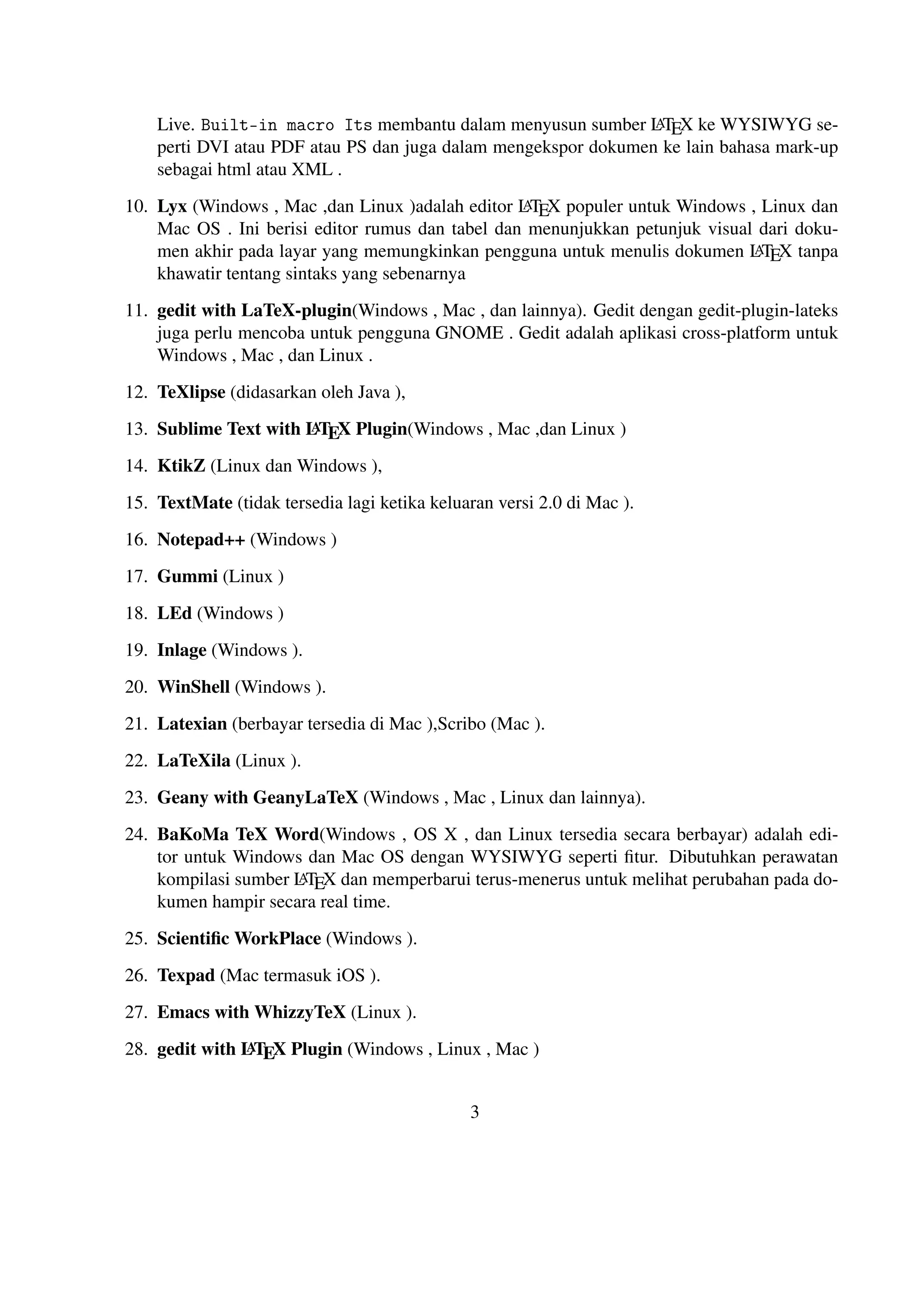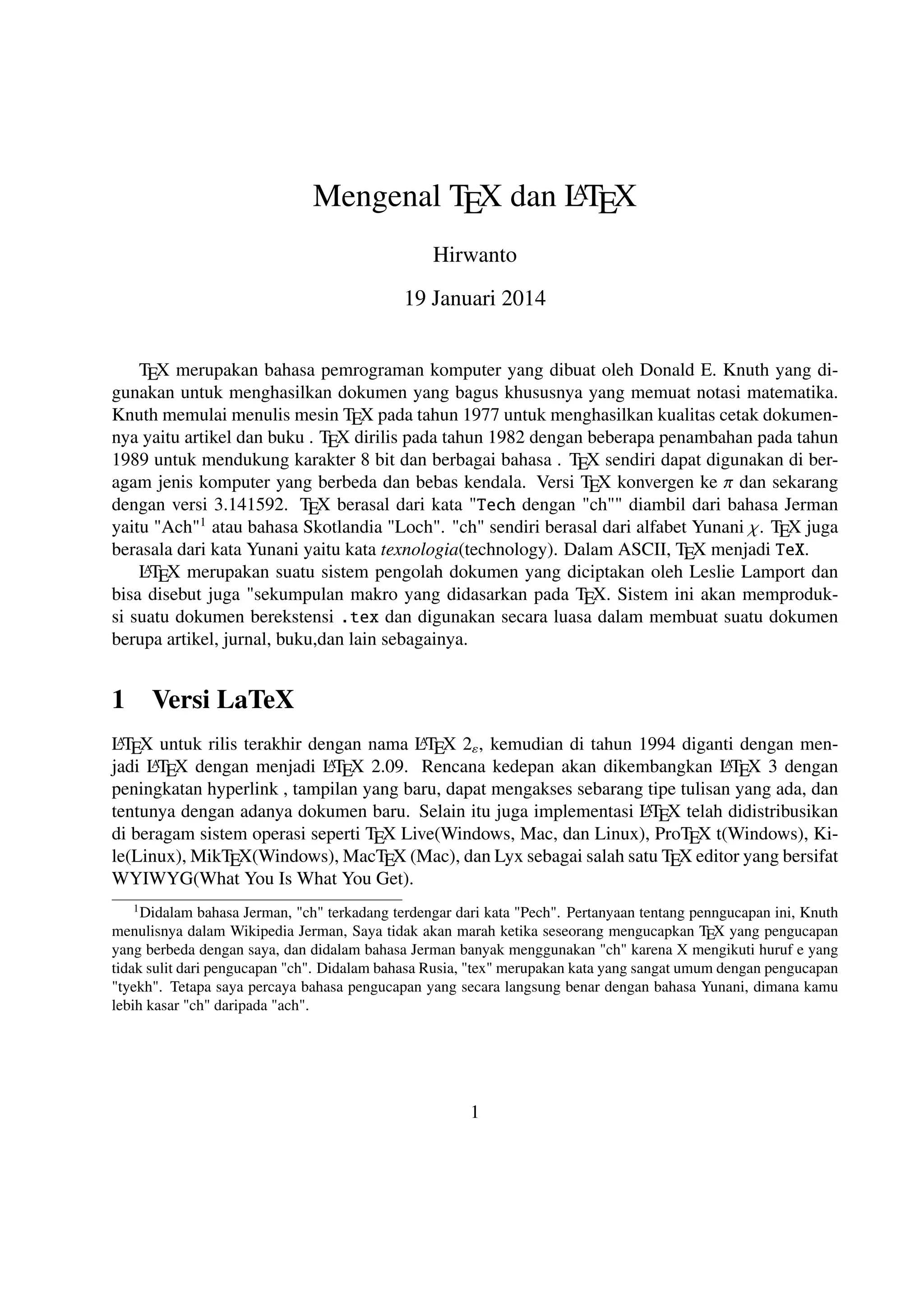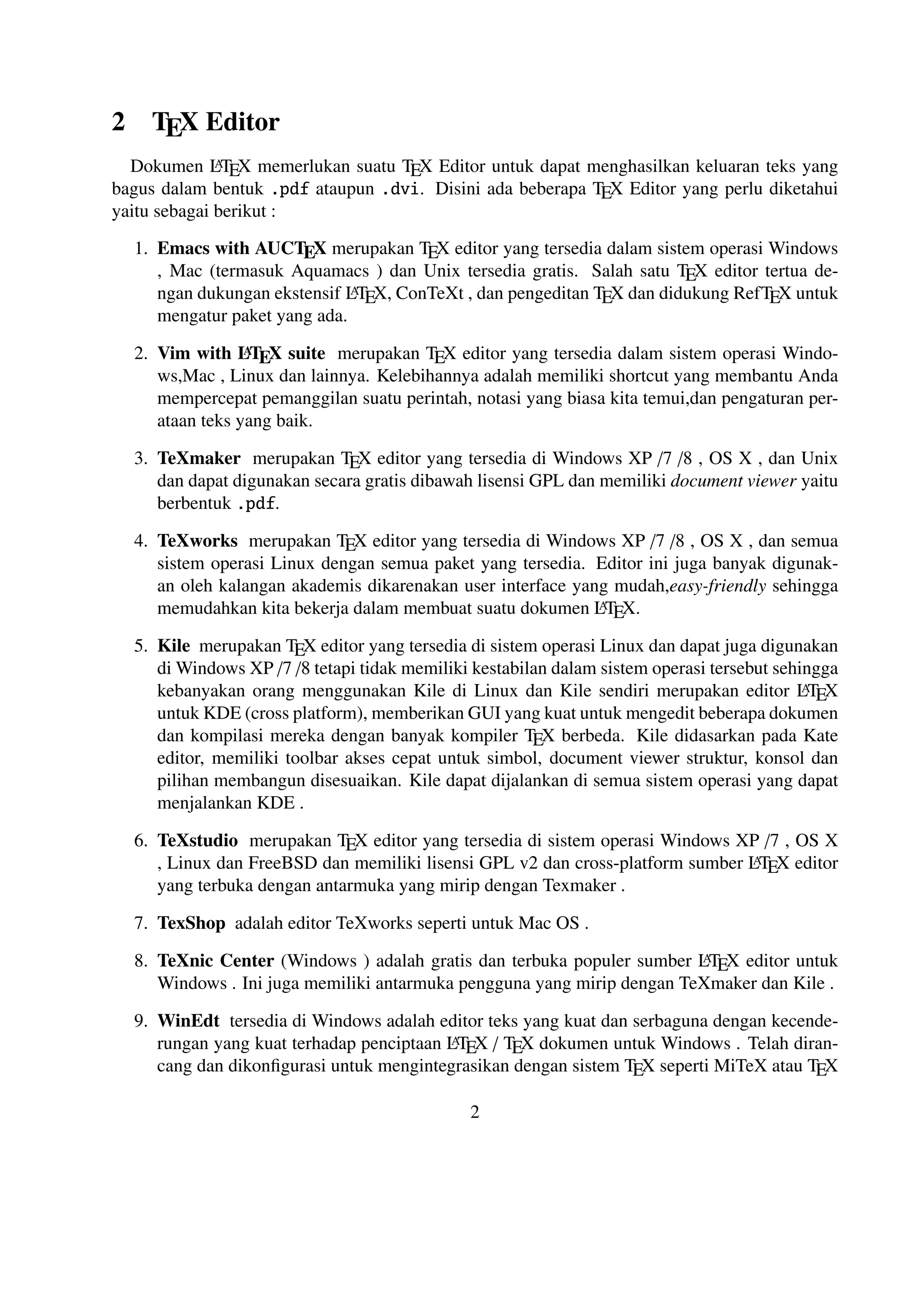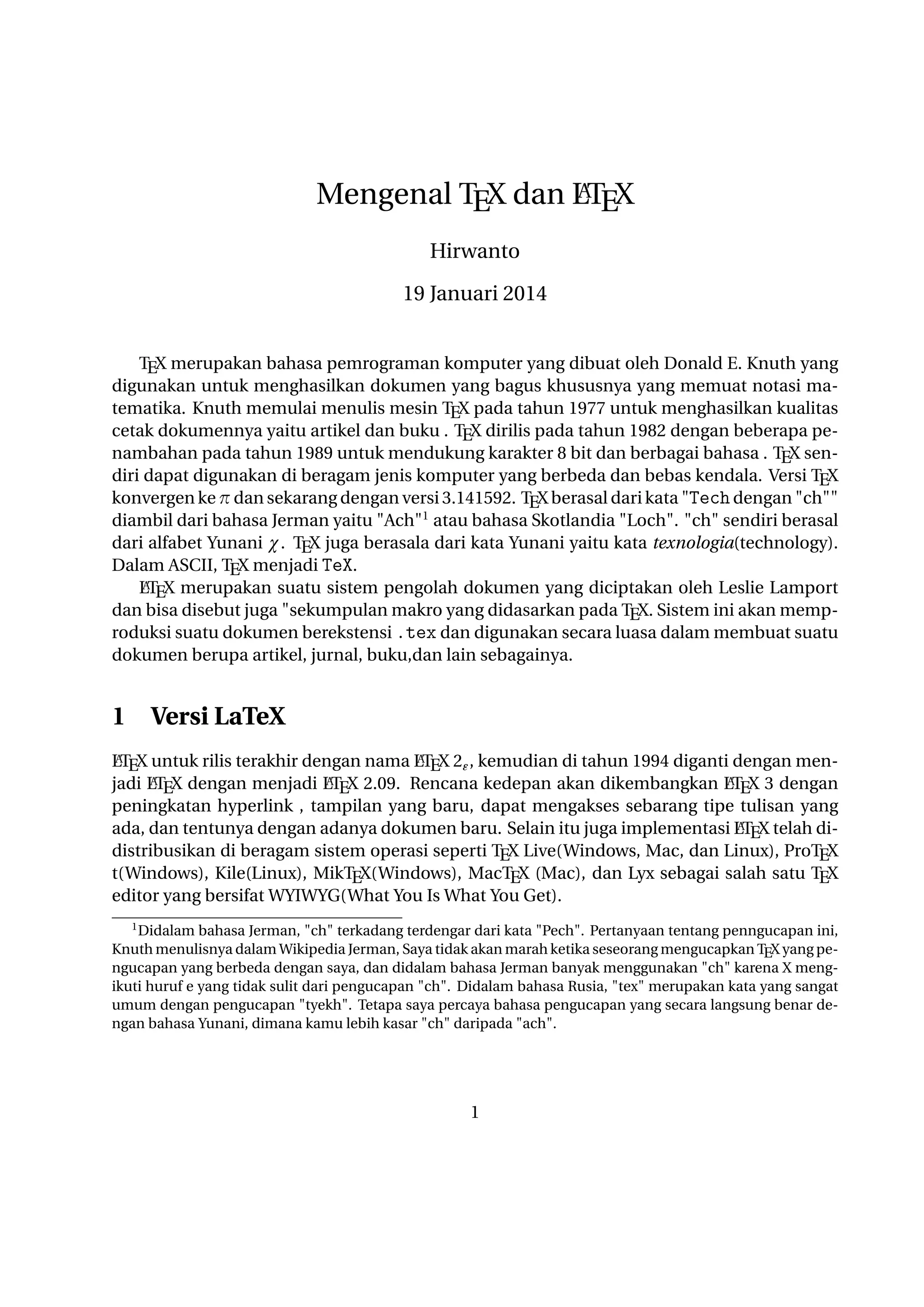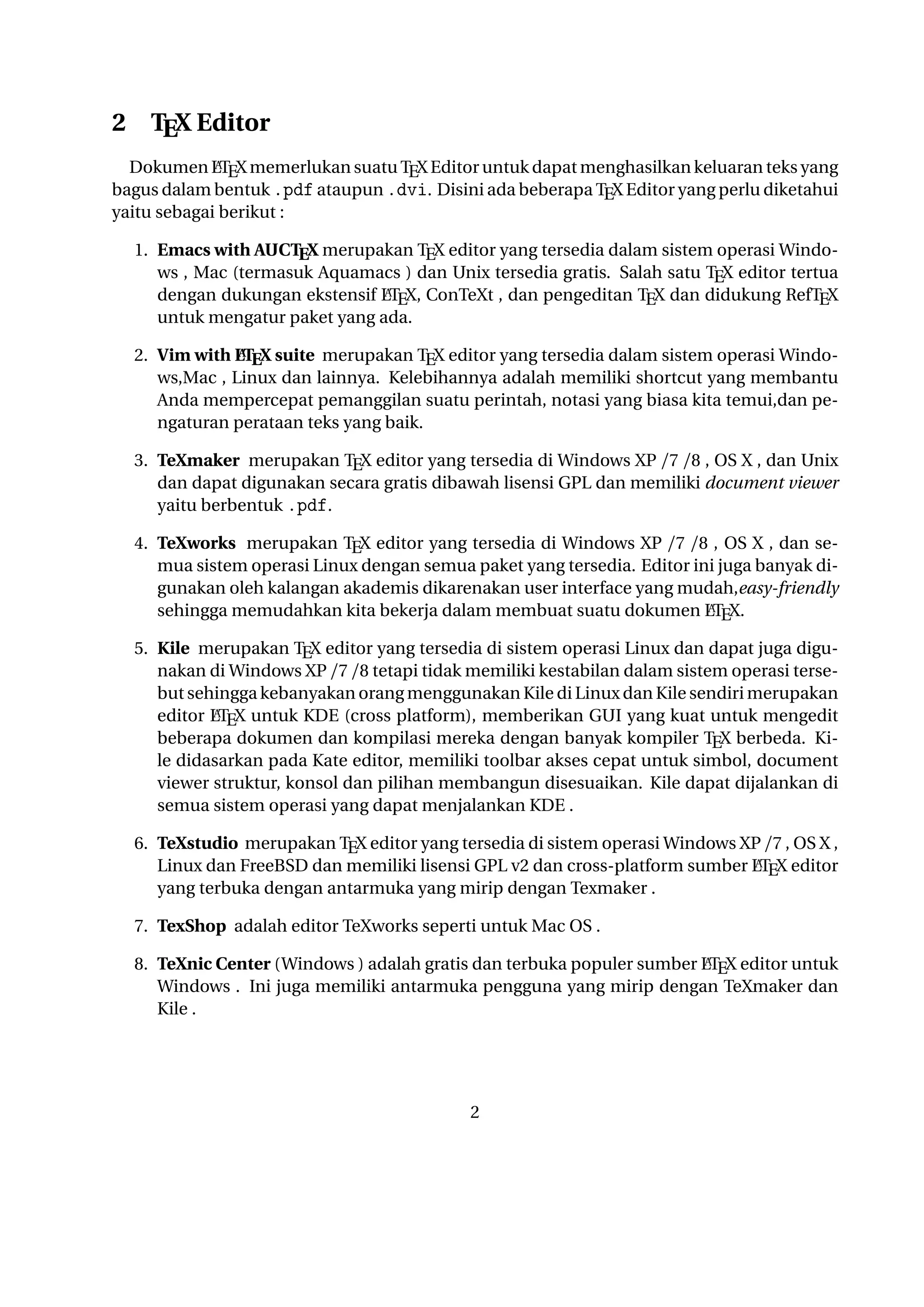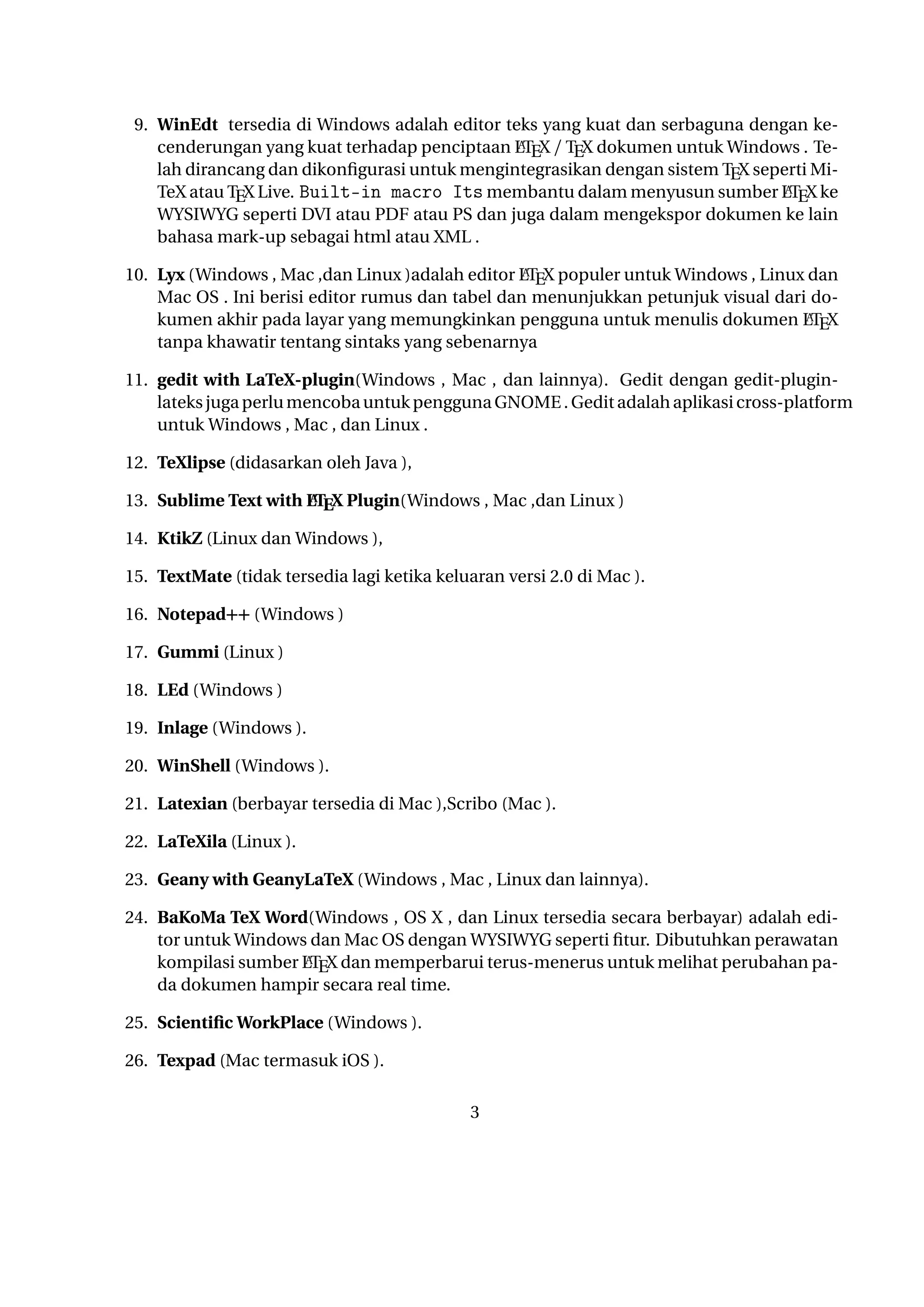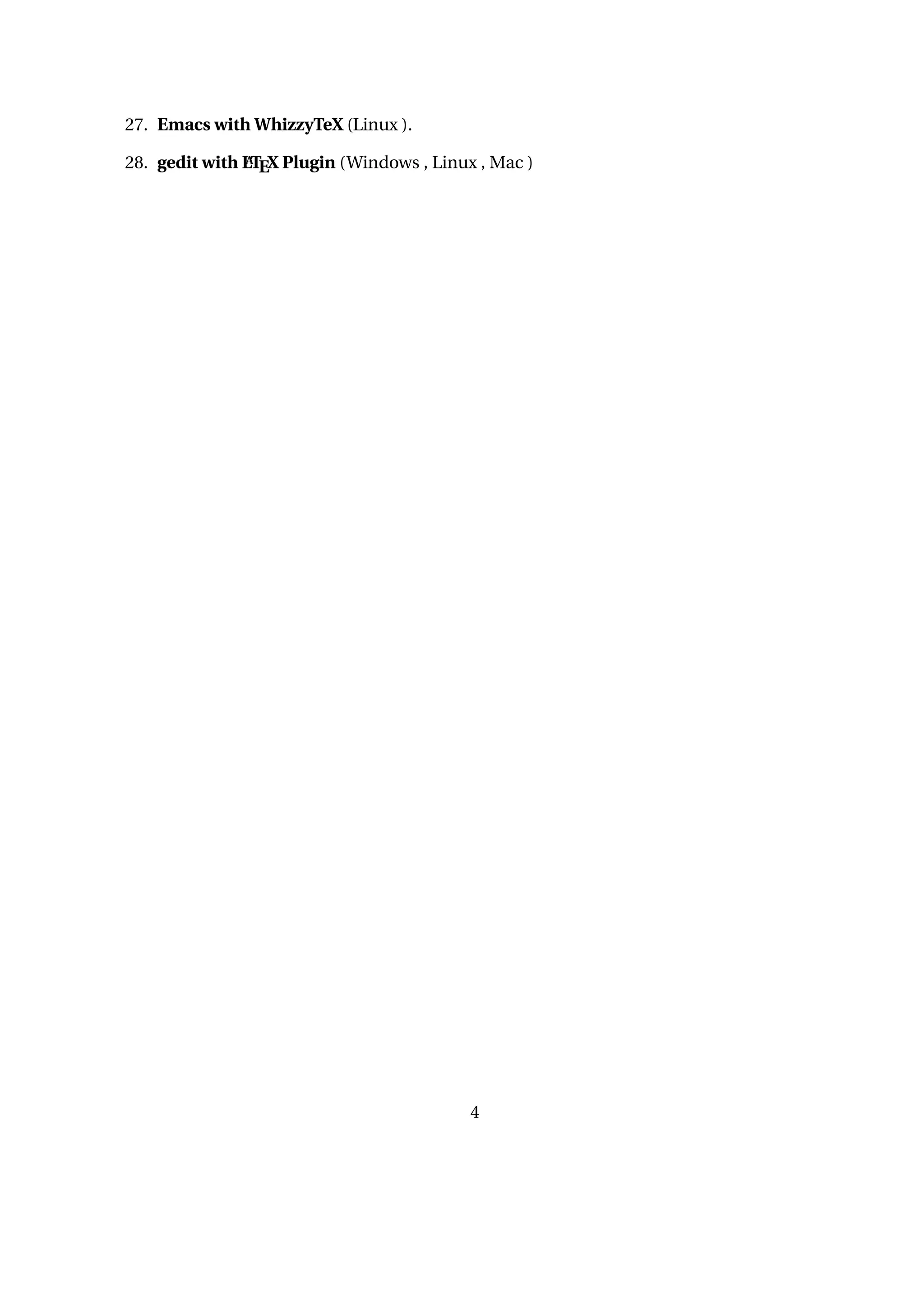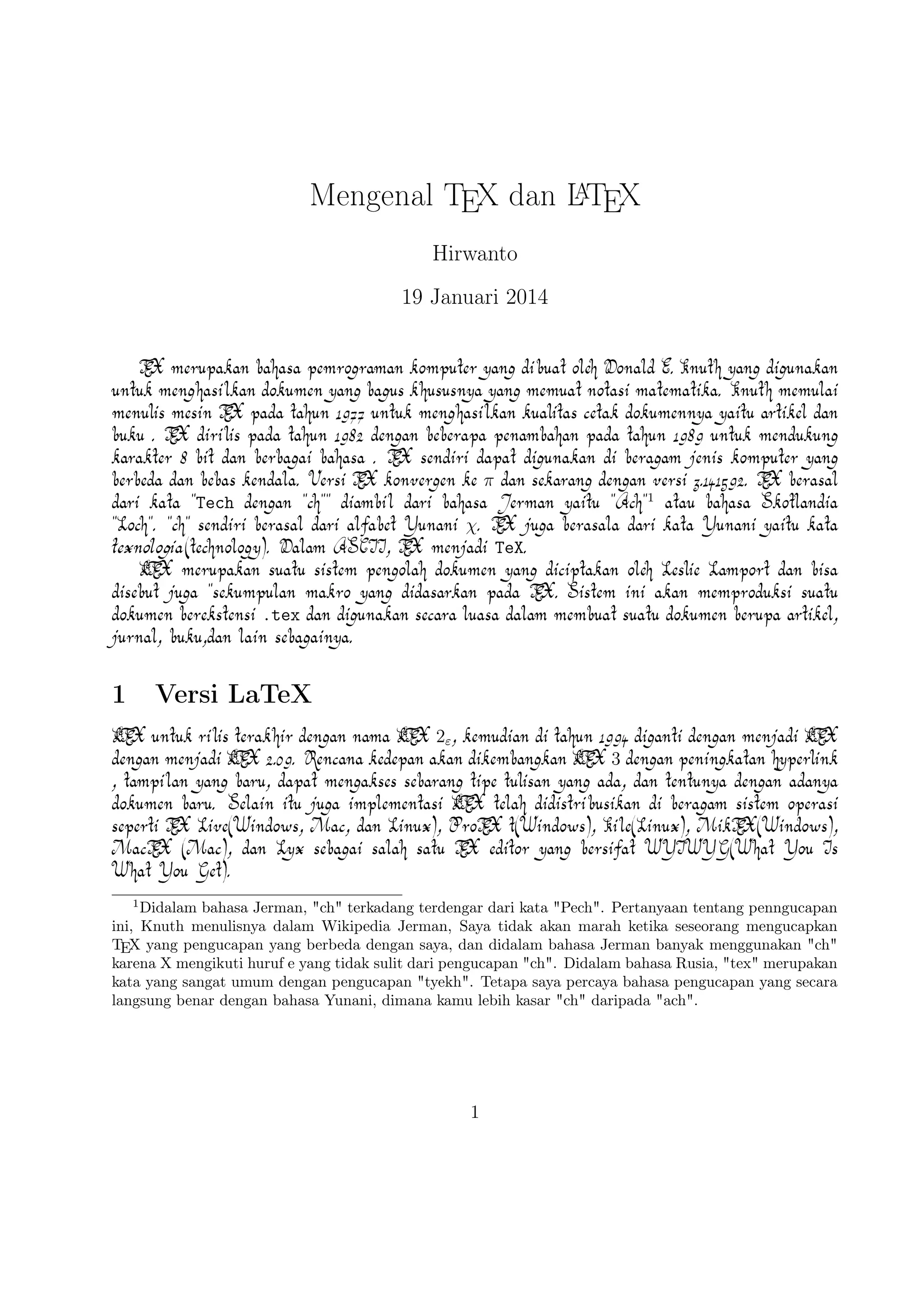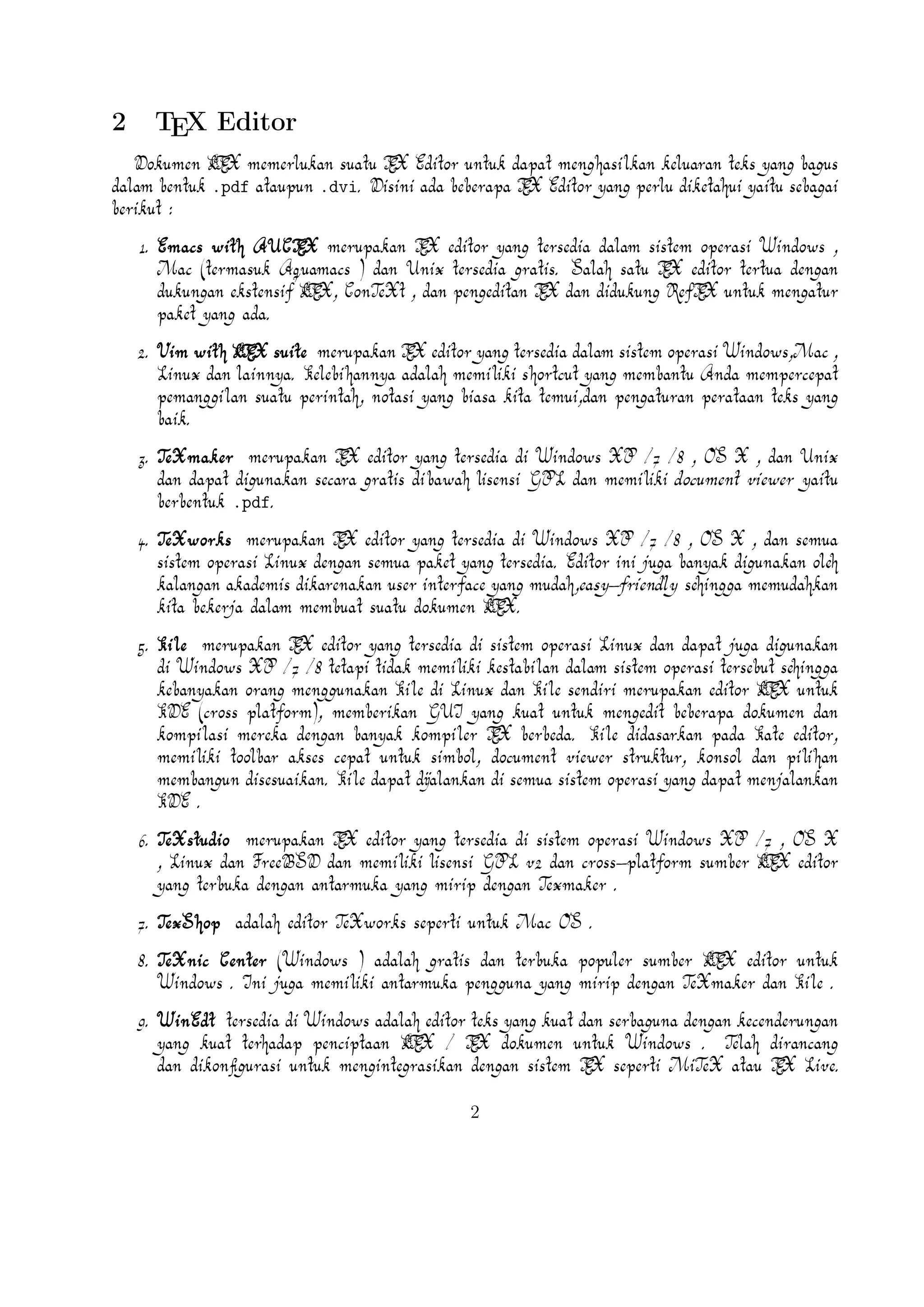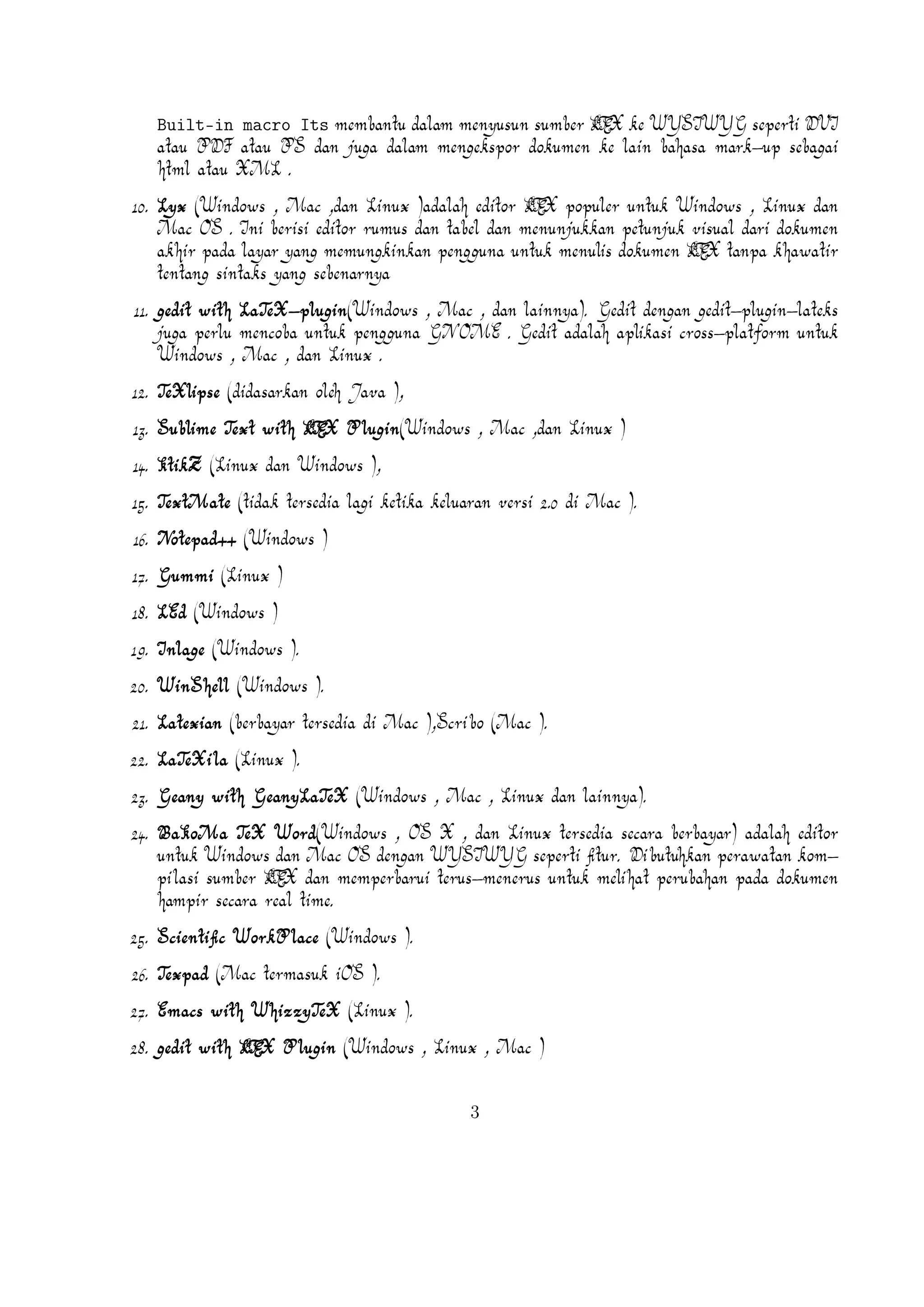
Mengenal TEX dan LTEX
Hirwanto
19 Januari 2014
TEX merupakan bahasa pemrograman komputer yang dibuat oleh Donald E. Knuth yang
digunakan untuk menghasilkan dokumen yang bagus khususnya yang memuat notasi matematika. Knuth memulai menulis mesin TEX pada tahun 1977 untuk menghasilkan kualitas cetak
dokumennya yaitu artikel dan buku . TEX dirilis pada tahun 1982 dengan beberapa penambahan pada tahun 1989 untuk mendukung karakter 8 bit dan berbagai bahasa . TEX sendiri dapat
digunakan di beragam jenis komputer yang berbeda dan bebas kendala. Versi TEX konvergen
ke π dan sekarang dengan versi 3.141592. TEX berasal dari kata "Tech dengan "ch"" diambil
dari bahasa Jerman yaitu "Ach"1 atau bahasa Skotlandia "Loch". "ch" sendiri berasal dari alfabet
Yunani χ. TEX juga berasala dari kata Yunani yaitu kata texnologia(technology). Dalam ASCII,
TEX menjadi TeX.
A
LTEX merupakan suatu sistem pengolah dokumen yang diciptakan oleh Leslie Lamport dan
bisa disebut juga "sekumpulan makro yang didasarkan pada TEX. Sistem ini akan memproduksi
suatu dokumen berekstensi .tex dan digunakan secara luasa dalam membuat suatu dokumen
berupa artikel, jurnal, buku,dan lain sebagainya.
Versi LTEX
LTEX untuk rilis terakhir dengan nama LTEX 2ε , kemudian di tahun 1994 diganti dengan menjadi
A X dengan menjadi LT X 2.09. Rencana kedepan akan dikembangkan LT X 3 dengan peningA
katan hyperlink , tampilan yang baru, dapat mengakses sebarang tipe tulisan yang ada, dan
tentunya dengan adanya dokumen baru. Selain itu juga implementasi LTEX telah didistribusikan di beragam sistem operasi seperti TEX Live(Windows, Mac, dan Linux), ProTEX t(Windows),
Kile(Linux), MikTEX(Windows), MacTEX (Mac), dan Lyx sebagai salah satu TEX editor yang bersifat WYIWYG(What You Is What You Get).
Didalam bahasa Jerman, "ch" terkadang terdengar dari kata "Pech". Pertanyaan tentang penngucapan ini, Knuth
menulisnya dalam Wikipedia Jerman, Saya tidak akan marah ketika seseorang mengucapkan TEX yang pengucapan
yang berbeda dengan saya, dan didalam bahasa Jerman banyak menggunakan "ch" karena X mengikuti huruf e
yang tidak sulit dari pengucapan "ch". Didalam bahasa Rusia, "tex" merupakan kata yang sangat umum dengan
pengucapan "tyekh". Tetapa saya percaya bahasa pengucapan yang secara langsung benar dengan bahasa Yunani,
dimana kamu lebih kasar "ch" daripada "ach".
TEX Editor
Dokumen LTEX memerlukan suatu TEX Editor untuk dapat menghasilkan keluaran teks yang
bagus dalam bentuk .pdf ataupun .dvi. Disini ada beberapa TEX Editor yang perlu diketahui
yaitu sebagai berikut :
1. Emacs with AUCTEX merupakan TEX editor yang tersedia dalam sistem operasi Windows
, Mac (termasuk Aquamacs ) dan Unix tersedia gratis. Salah satu TEX editor tertua dengan
dukungan ekstensif LTEX, ConTeXt , dan pengeditan TEX dan didukung RefTEX untuk
mengatur paket yang ada.
2. Vim with LTEX suite merupakan TEX editor yang tersedia dalam sistem operasi Windows,Mac , Linux dan lainnya. Kelebihannya adalah memiliki shortcut yang membantu Anda
mempercepat pemanggilan suatu perintah, notasi yang biasa kita temui,dan pengaturan
perataan teks yang baik.
3. TeXmaker merupakan TEX editor yang tersedia di Windows XP /7 /8 , OS X , dan Unix
yaitu berbentuk .pdf.
4. TeXworks merupakan TEX editor yang tersedia di Windows XP /7 /8 , OS X , dan semua
sistem operasi Linux dengan semua paket yang tersedia. Editor ini juga banyak digunakan
oleh kalangan akademis dikarenakan user interface yang mudah,easy-friendly sehingga
memudahkan kita bekerja dalam membuat suatu dokumen LTEX.
5. Kile merupakan TEX editor yang tersedia di sistem operasi Linux dan dapat juga digunakan di Windows XP /7 /8 tetapi tidak memiliki kestabilan dalam sistem operasi tersebut
sehingga kebanyakan orang menggunakan Kile di Linux dan Kile sendiri merupakan
editor LTEX untuk KDE (cross platform), memberikan GUI yang kuat untuk mengedit
beberapa dokumen dan kompilasi mereka dengan banyak kompiler TEX berbeda. Kile
didasarkan pada Kate editor, memiliki toolbar akses cepat untuk simbol, document viewer
struktur, konsol dan pilihan membangun disesuaikan. Kile dapat dijalankan di semua
sistem operasi yang dapat menjalankan KDE .
6. TeXstudio merupakan TEX editor yang tersedia di sistem operasi Windows XP /7 , OS X
, Linux dan FreeBSD dan memiliki lisensi GPL v2 dan cross-platform sumber LTEX editor
yang terbuka dengan antarmuka yang mirip dengan Texmaker .
7. TexShop adalah editor TeXworks seperti untuk Mac OS .
8. TeXnic Center (Windows ) adalah gratis dan terbuka populer sumber LTEX editor untuk
Windows . Ini juga memiliki antarmuka pengguna yang mirip dengan TeXmaker dan
digunakan untuk menghasilkan dokumen yang bagus khususnya yang memuat notasi matematika. Knuth memulai menulis mesin TEX pada tahun 1977 untuk menghasilkan kualitas
cetak dokumennya yaitu artikel dan buku . TEX dirilis pada tahun 1982 dengan beberapa
penambahan pada tahun 1989 untuk mendukung karakter 8 bit dan berbagai bahasa . TEX
sendiri dapat digunakan di beragam jenis komputer yang berbeda dan bebas kendala. Versi TEX konvergen ke π dan sekarang dengan versi 3.141592. TEX berasal dari kata Tech